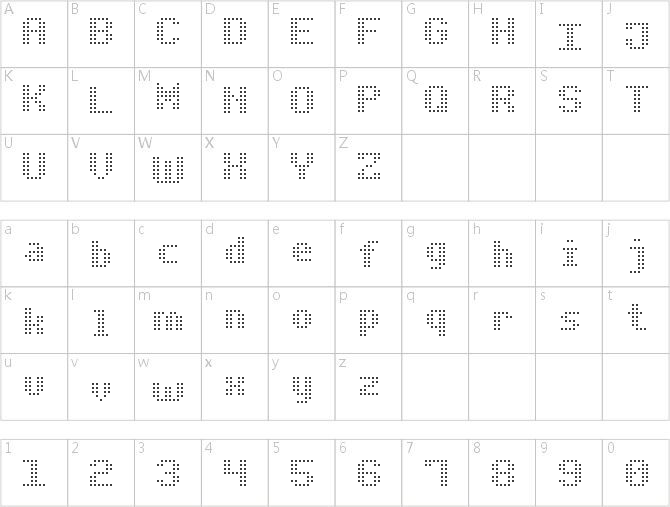
bold_dot_digital-7 詳情頁
字體名稱: bold_do
bold_dot_digital-7
bold_dot_digital-7介紹
bold_dot_digital-7字體字庫是一款讓人賞心悅目、百看不厭的英文字體,適合各類廣告和產(chǎn)品包裝設計應用,字體大小0.09MB,格式為ttf字體,上傳用戶是IceNet,作者/版權方為未知